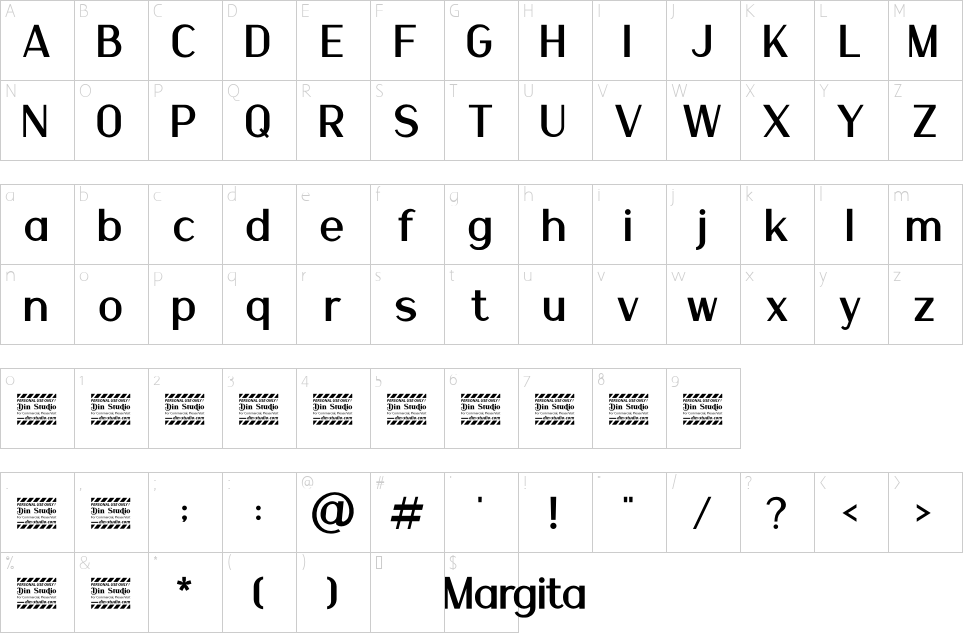
A fonte ‘Margita Font’ é uma escolha perfeita para projetos de design gráfico que buscam uma aparência elegante e versátil. Criada pela Din Studio, esta fonte é uma ótima opção para quem busca uma fonte de texto moderna e sofisticada. Com seu design minimalista e elegante, a Margita pode ser usada em diversas aplicações, desde e-mails pessoais até materiais publicitários. O design foi pensado para proporcionar um acabamento profissional e moderno, ajudando a destacar seus designs. Com suas 4.581 downloads, a Margita está se tornando uma opção popular para quem busca uma fonte de qualidade. Se você está procurando por uma fonte grata com uma aparência única e de alto nível, a ‘Margita Font’ pode ser a escolha perfeita para seu próximo projeto.